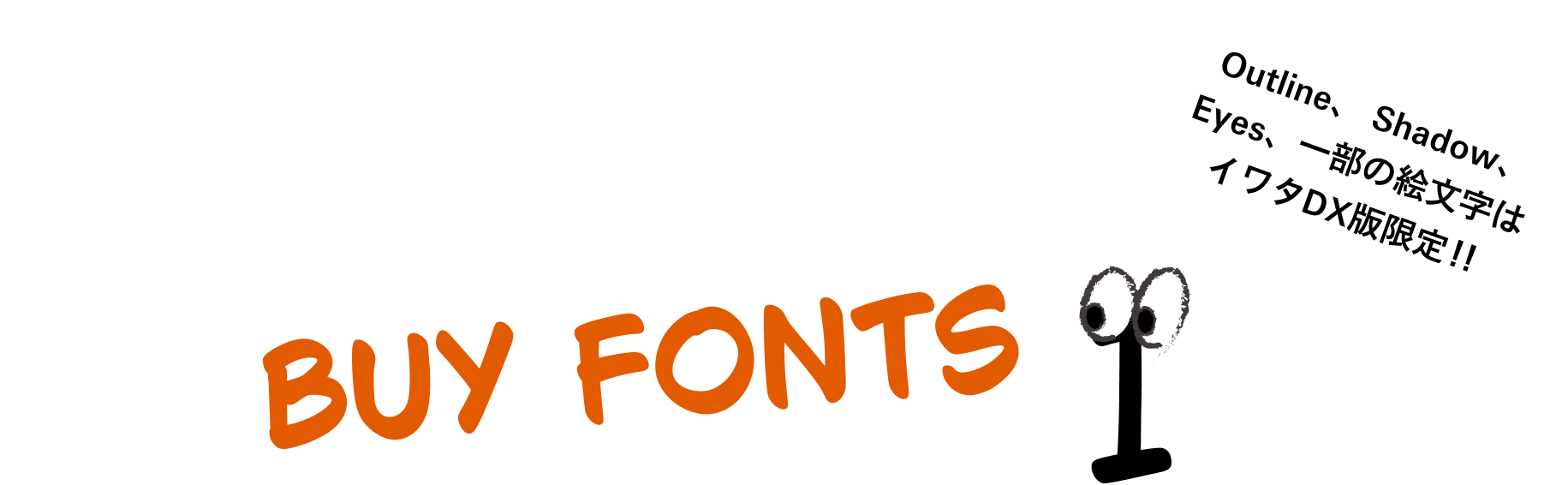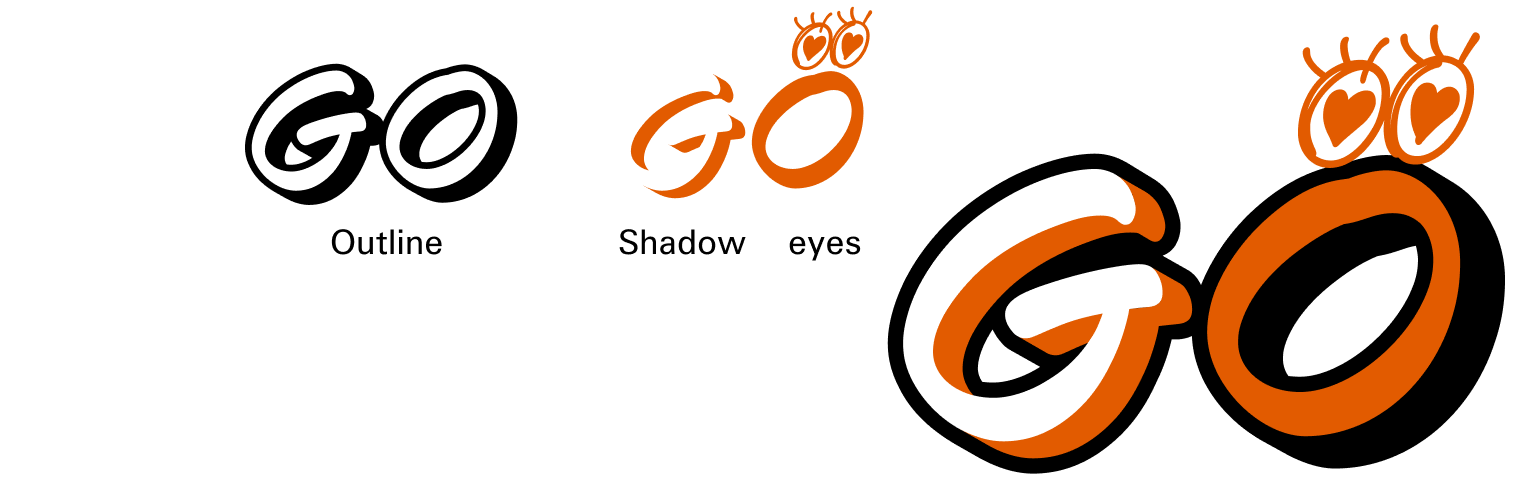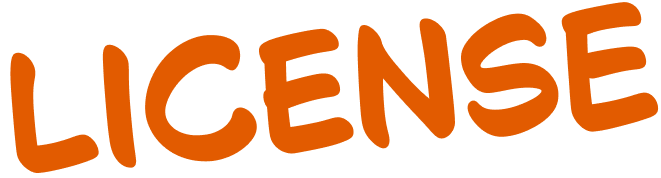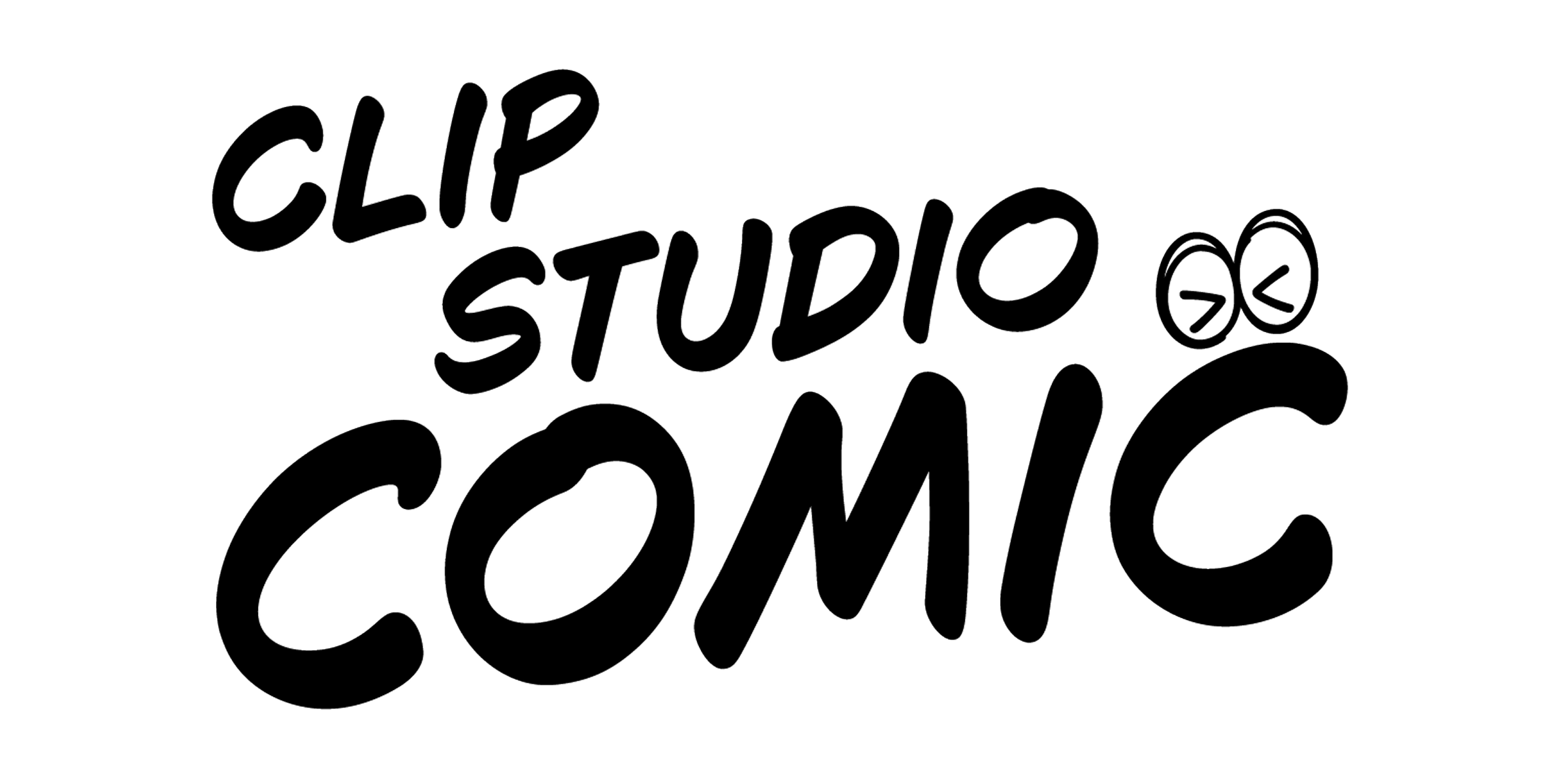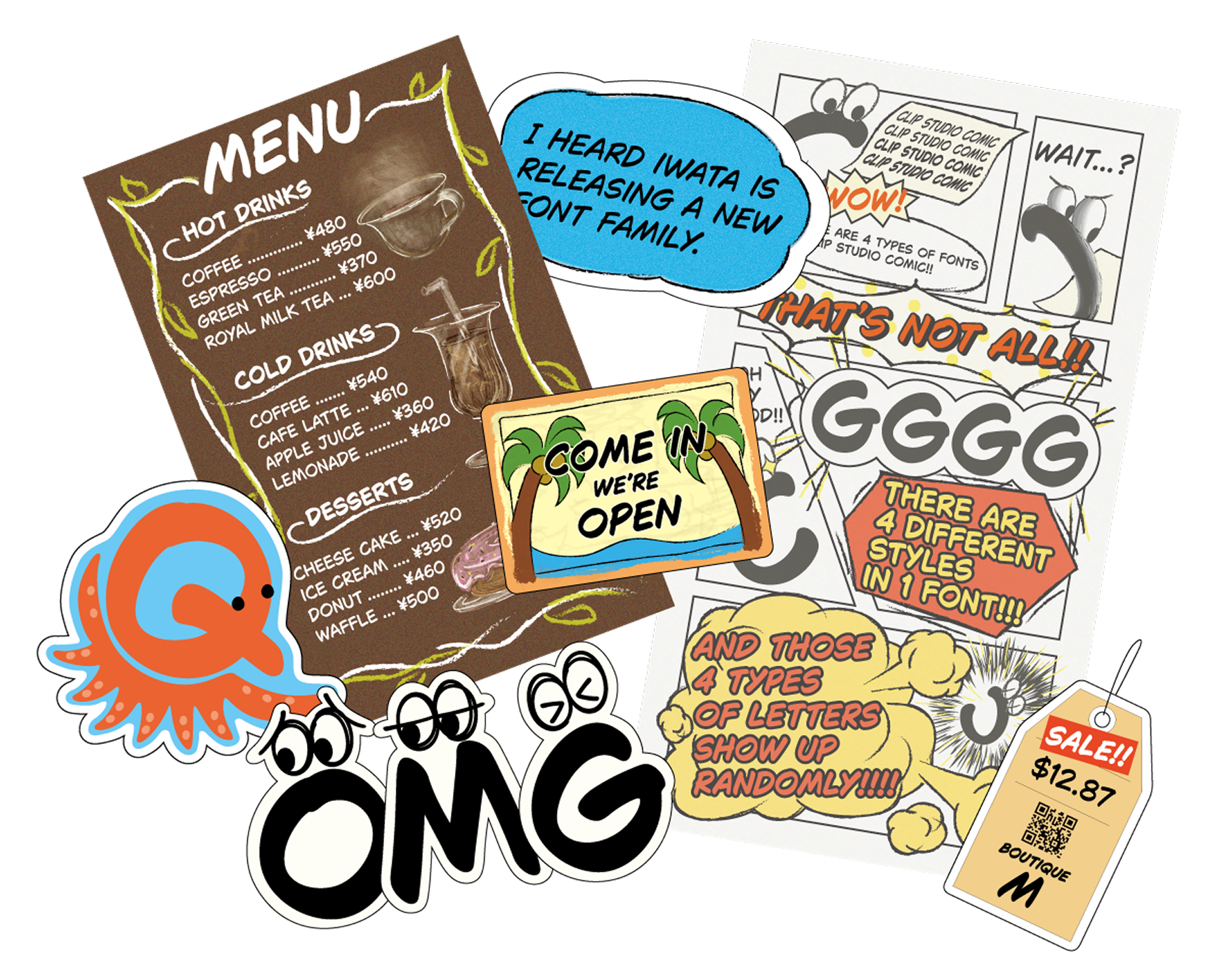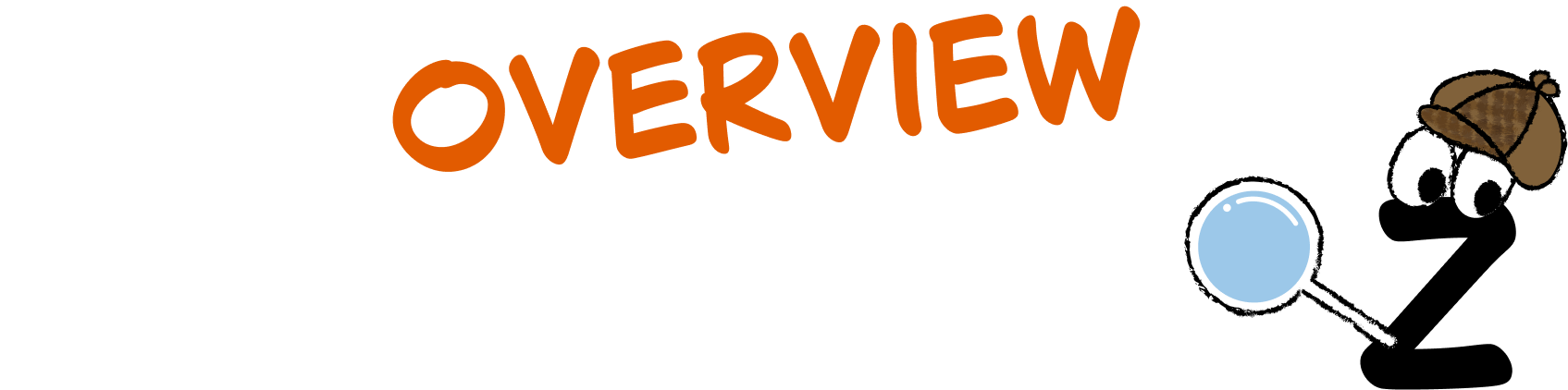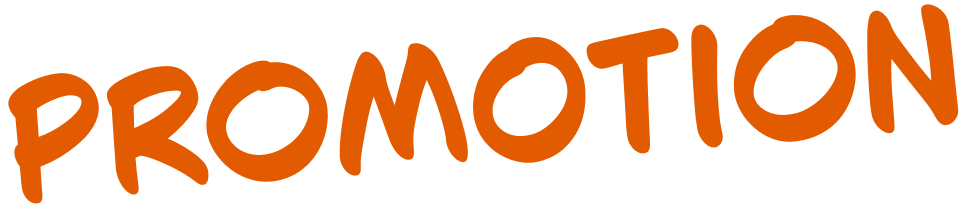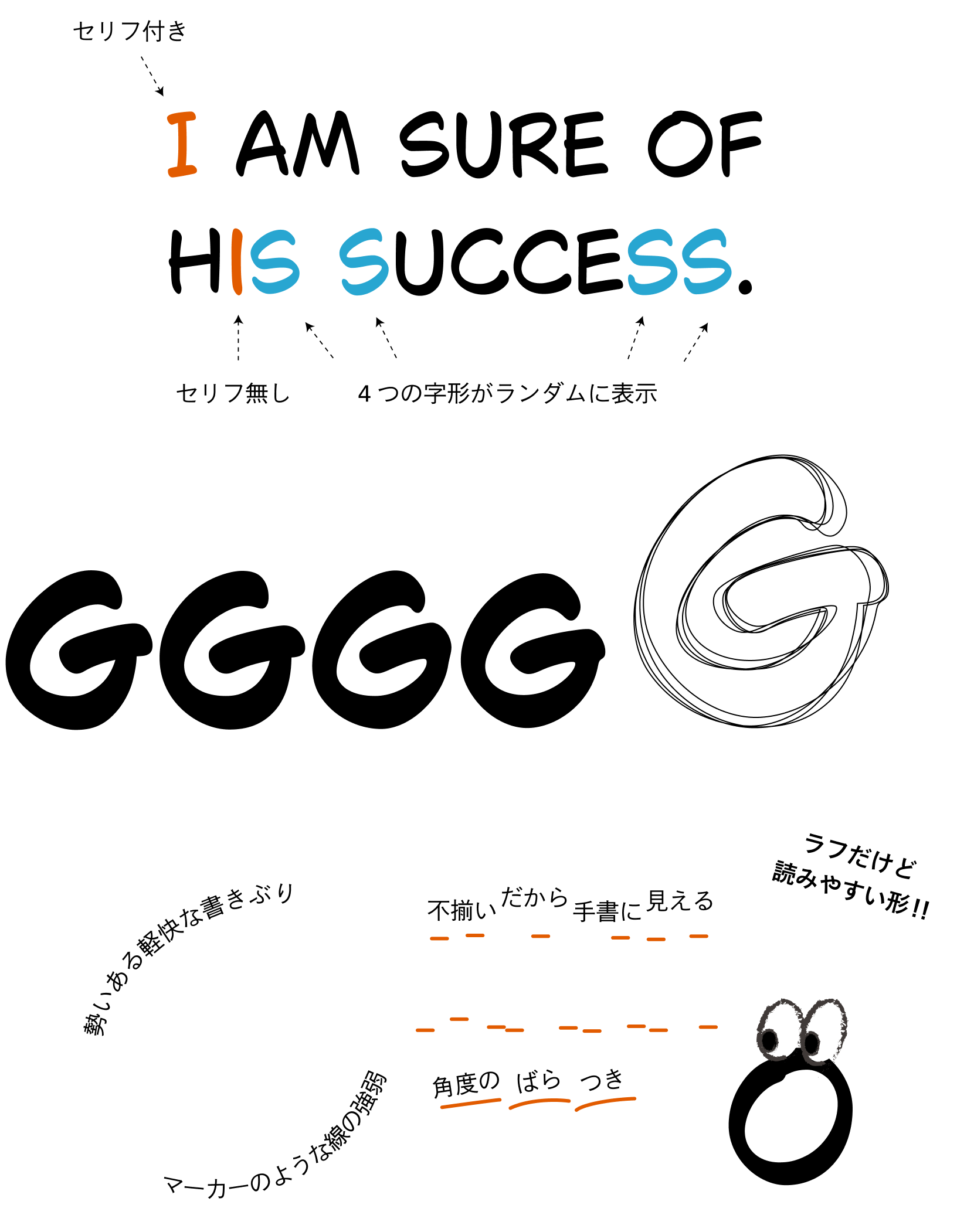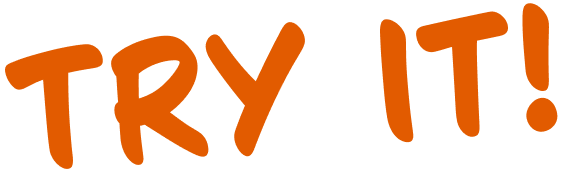
まるで手書き!?
文字それぞれに4つの字形を収録。入力する度にランダム表示され、まるで手書きのような組版を実現。ネイティブユーザーからの希望が多かった、一人称の「I」に自動でセリフが付く機能を搭載。
多言語に対応!
フランス語、スペイン語、ドイツ語、イタリア語などラテンアルファベット圏の多くの言語表記をカバー。
使い方は無限大!
「CLIP STUDIO PAINT Ver.3.0」以降標準搭載版とイワタDX版をご用意。イワタDX版は追加絵文字やOutlineなどのバリエーションが仲間入りしてパワーアップ。組み合わせて使うことで表現の幅がさらに広がる。
| Iwata Clip Studio Comic |
| Iwata Clip Studio Comic Outline |
| Iwata Clip Studio Comic Shadow |
| Iwata Clip Studio Comic eyes |
| Clip Studio Comic |